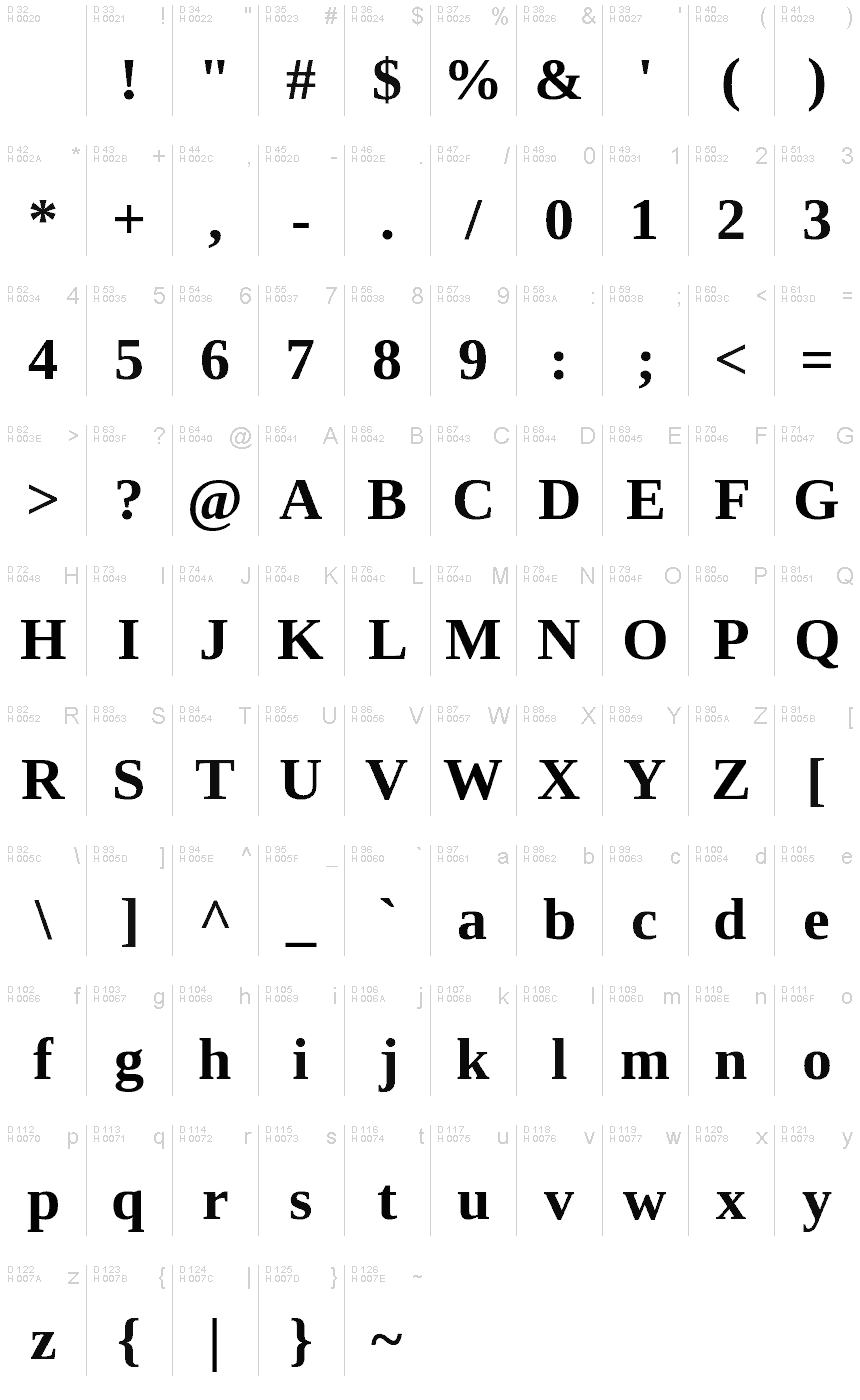
Liberation Serif Bold è un carattere graziato classico e gratuito, con il sapore familiare dei libri e dei giornali. Le lettere combinano un peso solido con grazie precise e forme compatte e decise, per un aspetto formale che non risulta mai rigido.
È ideale per titoli editoriali, copertine di libri, rapporti, poster e branding tradizionale, specialmente quando si cerca un tono tipografico classico invece di un effetto stilizzato. Essendo un font gratuito, è perfetto anche per citazioni, incipit di capitoli e brevi titoli web: il ritmo delle sue grazie in grassetto conferisce alle linee corte una presenza solida e autorevole.
Liberation Serif
Ascender Corporation
Steve Matteson